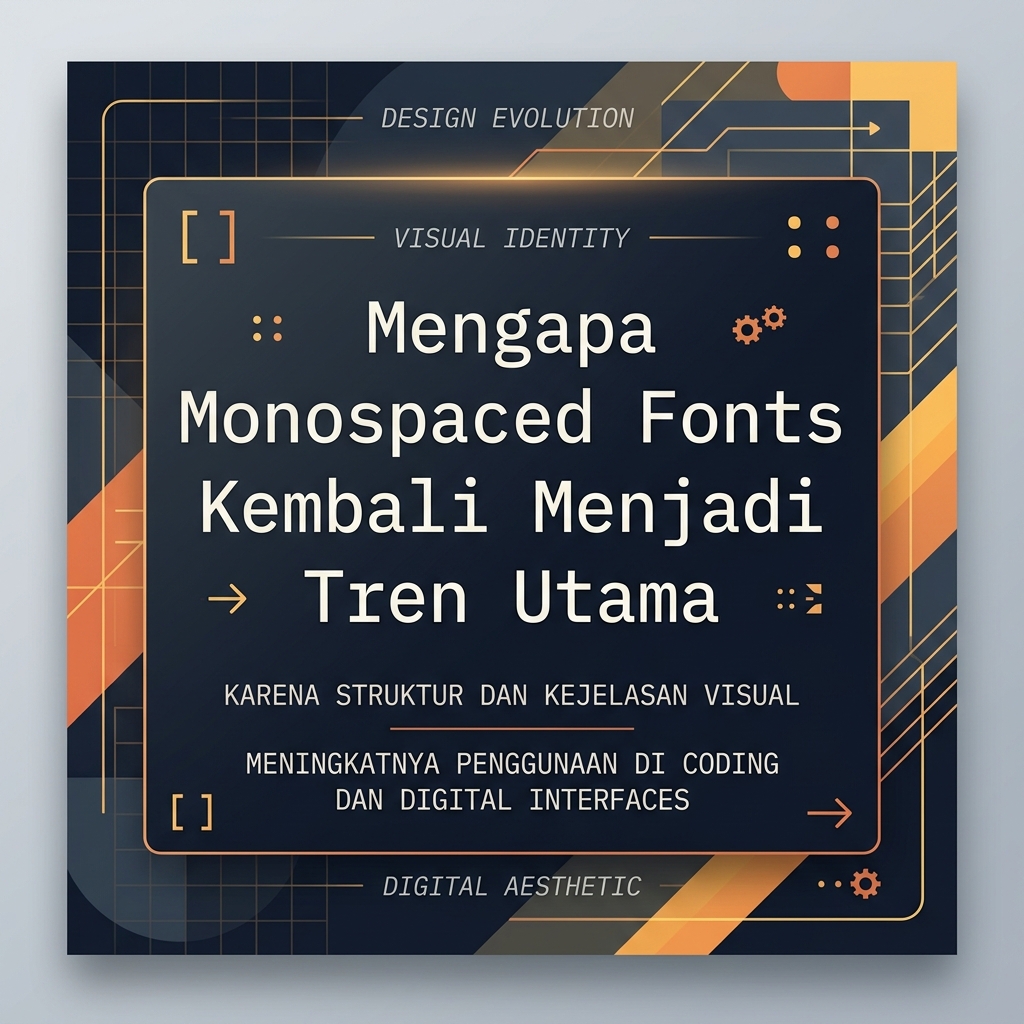
Mengapa Monospaced Fonts Kembali Menjadi Tren Utama
Gubuku – Kalau kamu perhatiin feed Instagram, konten TikTok, sampai website jualan brand lokal belakangan ini, ada satu tren visual yang mendadak muncul di mana-mana: font yang bentuknya kaku, berjarak rapi, dan kelihatan kayak hasil ketikan mesin tik tua atau baris kode programmer.
Yap, itulah Monospaced Fonts. Font yang tadinya dianggap “kuno” dan bikin bosan ini mendadak balik lagi dan jadi raja visual baru. Tapi, kenapa sih font zaman purba ini malah bikin Gen Z jatuh cinta?
1. Vibe Retro-Futurism yang “Estetik Parah” Gen Z paling pintar kalau soal gabungin hal-hal nostalgia sama sesuatu yang modern. Monospaced font memberikan sentuhan cyberpunk, retro-tech, dan Y2K yang kental banget. Font ini bikin desain kelihatan kayak layar komputer tahun 90-an tapi tetap terasa keren pas dipasang di poster digital atau feed sosial media.
2. Anti-Mainstream dan Jujur (Anti-Polished) Bosan enggak sih sama tren desain Corporate Memphis atau font minimalis (sans-serif) yang semuanya kelihatan seragam dan terlalu “sempurna”? Monospaced font hadir bawa karakter yang beda. Garis-garisnya yang mentah dan tegas ngasih kesan raw, jujur, dan berani tampil beda. Gen Z yang menjunjung tinggi autentisitas jelas lebih nempel sama estetika ini.
3. Nostalgia Koding dan Budaya Digital Buat generasi yang tumbuh besar di era internet, monospaced font punya tempat tersendiri di memori kolektif. Font ini identik sama terminal code, teks rahasia, hingga game retro. Pake font ini seolah-olah ngasih sinyal subculture yang paham estetika digital masa kini.
Rekomendasi Monospaced Font yang Wajib Kamu Coba
• Space Mono: Cocok buat judul poster atau header web yang mau kelihatan edgy.
• Courier Prime: Versi modern dari font mesin tik klasik, pas buat nuansa nostalgia.
• JetBrains Mono: Sangat bersih, gampang dibaca, dan ngasih kesan tech-savvy.
• IBM Plex Mono: Perpaduan sempurna antara kesan industrial dan desain profesional.
Dunia desain itu ibarat roda yang terus berputar. Monospaced font membuktikan kalau sesuatu yang dianggap jadul bisa kembali jadi tren paling panas kalau dikemas dengan sudut pandang yang tepat.